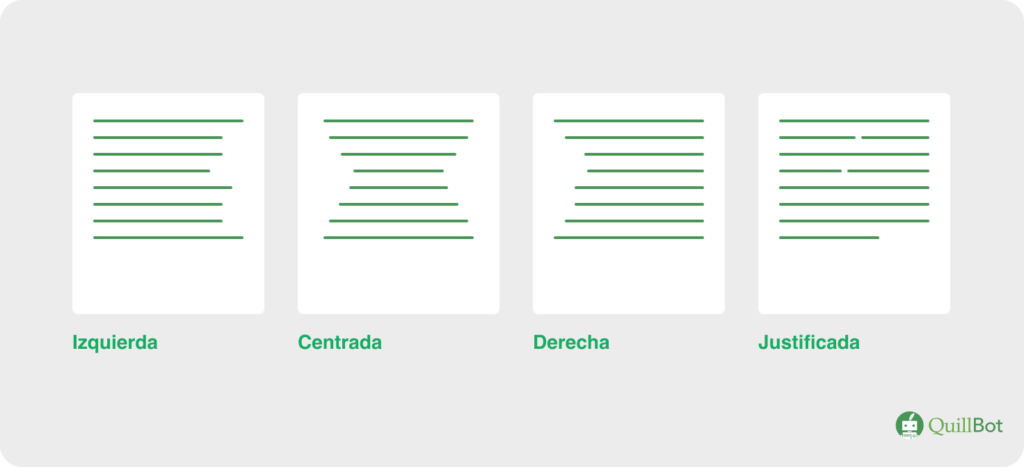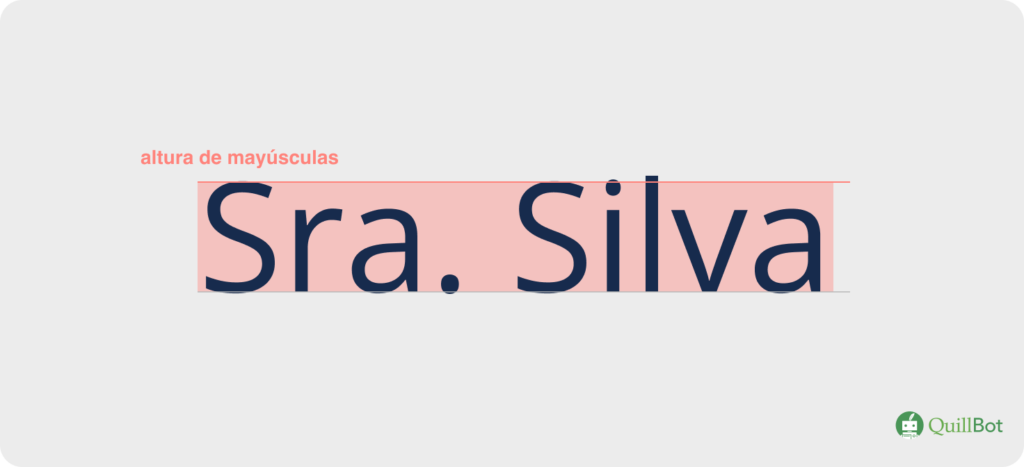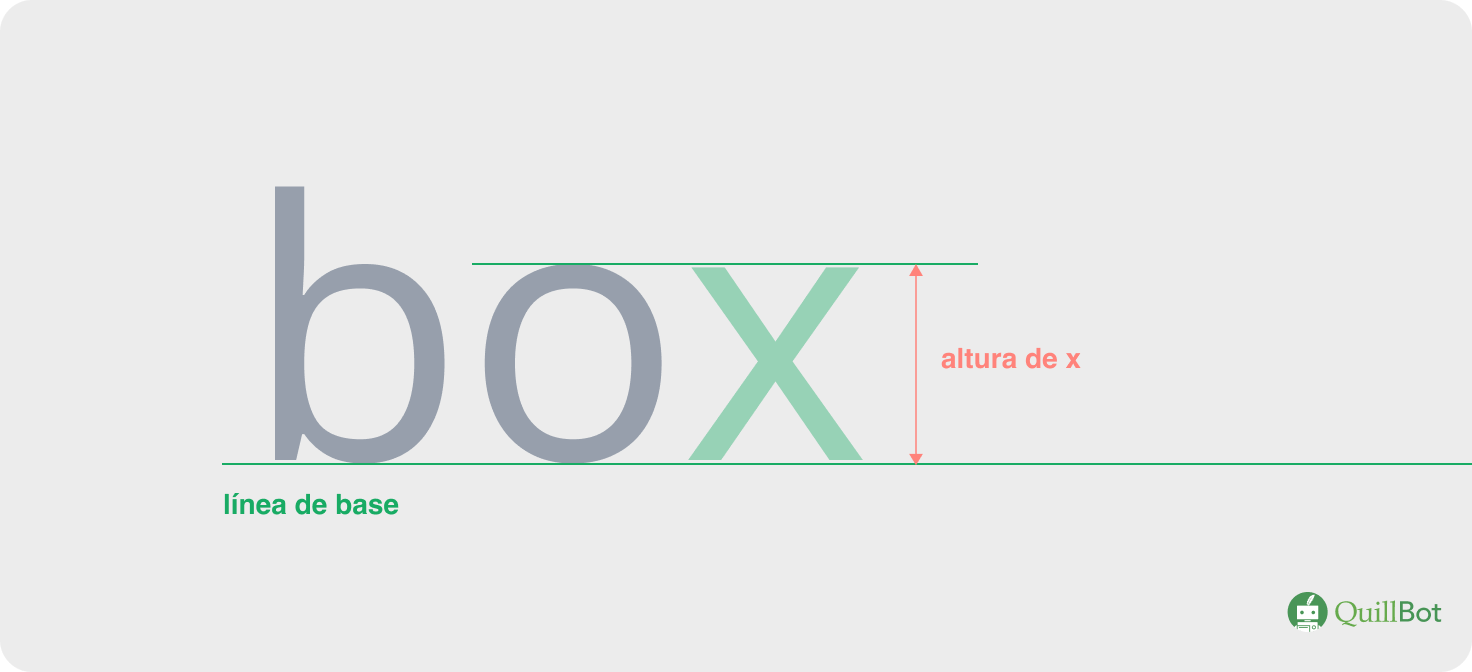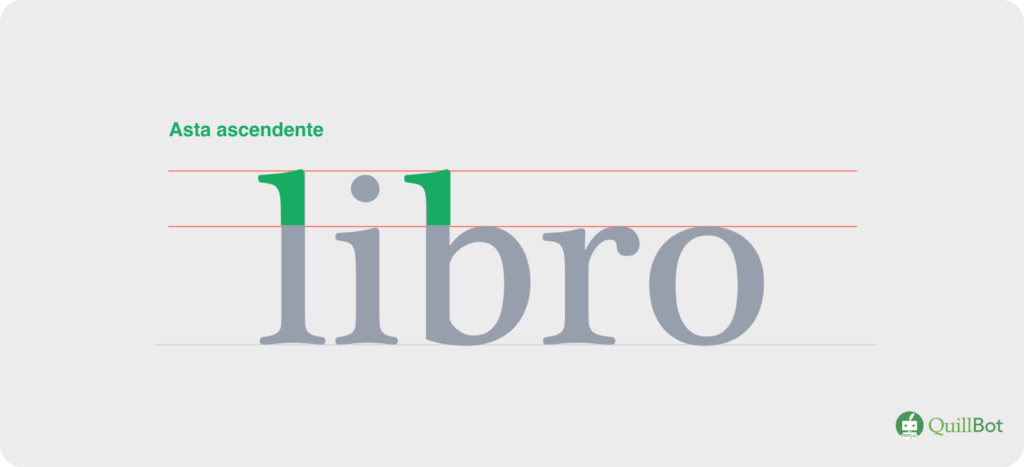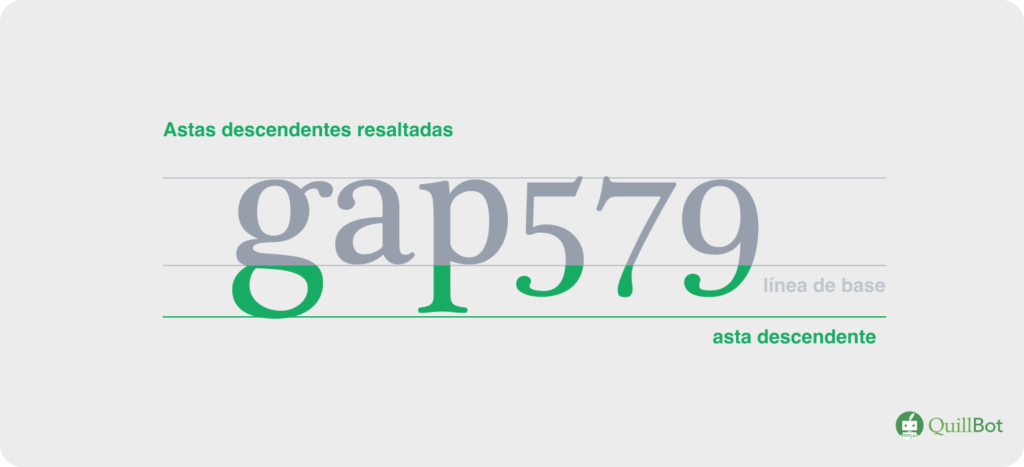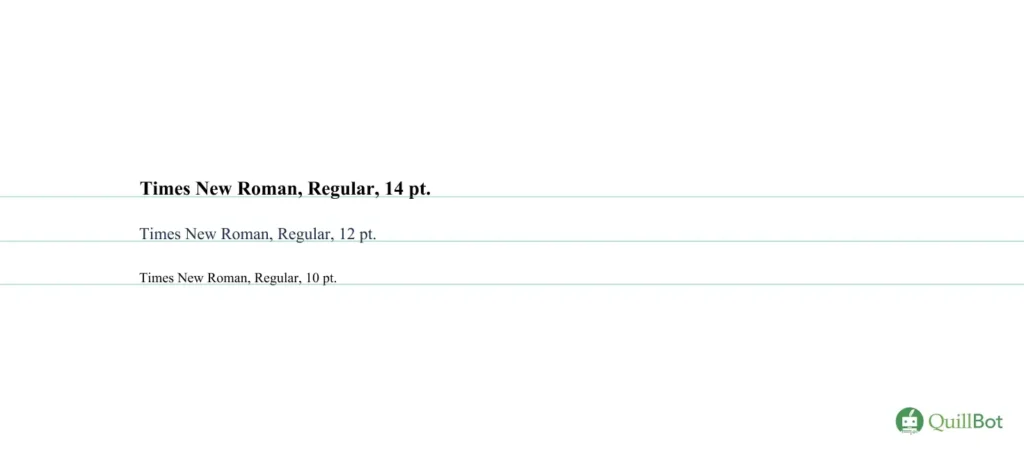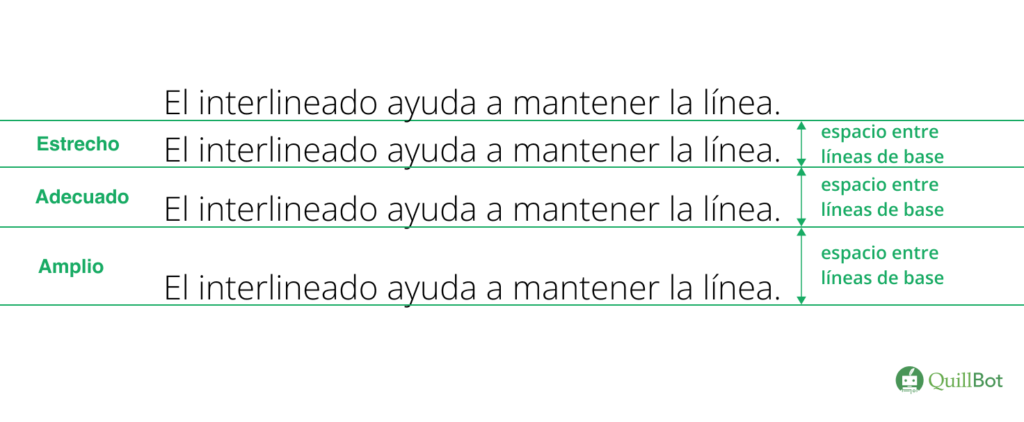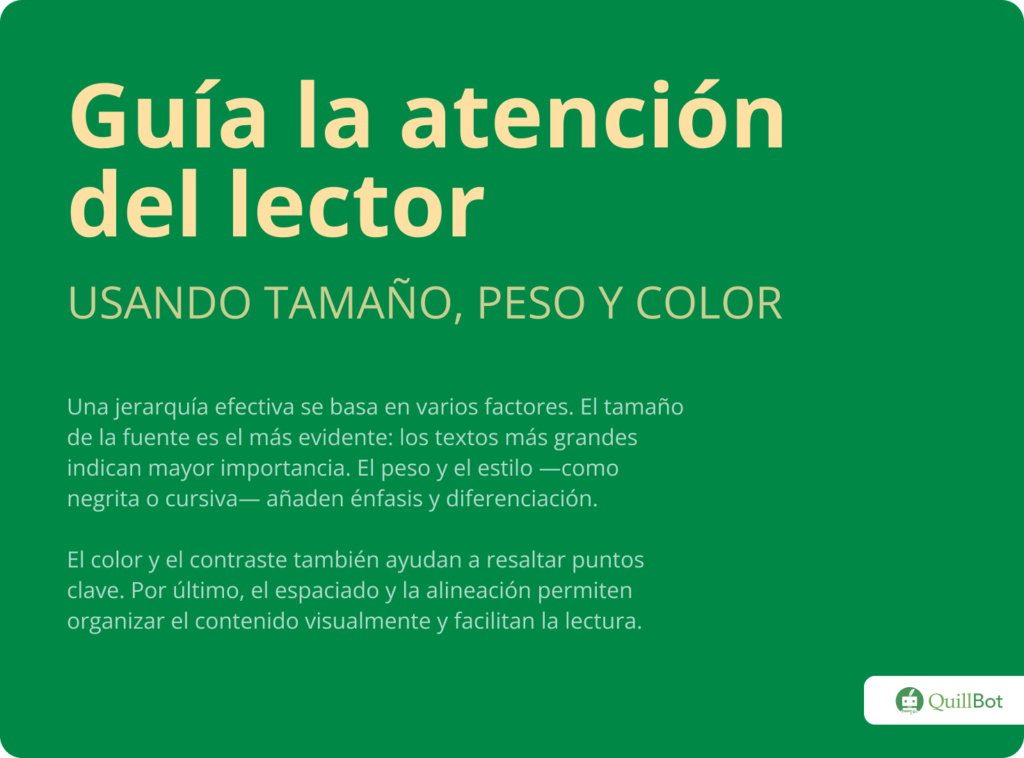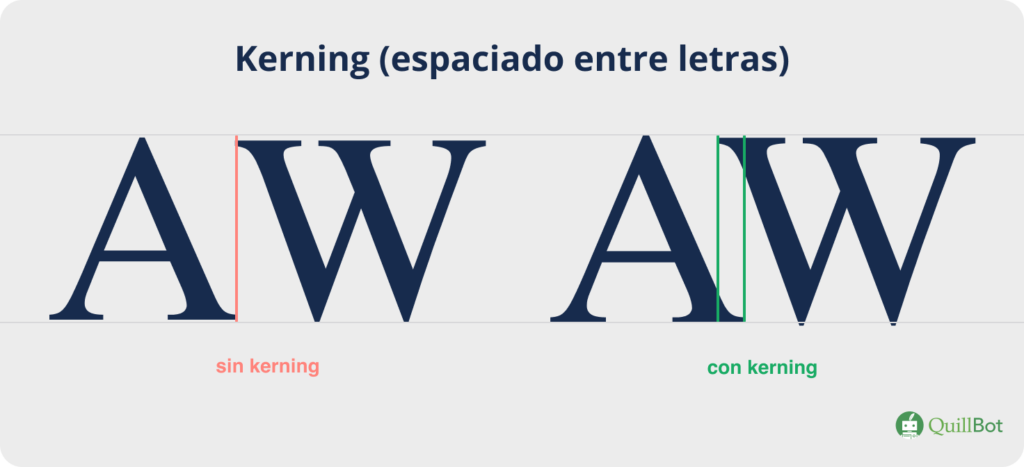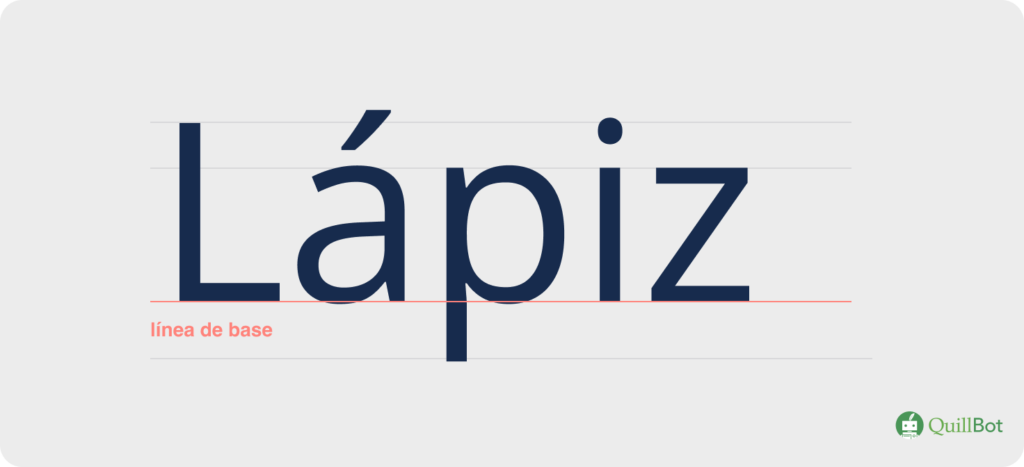
Tipografía | Significado, partes, tipos y ejemplos
La tipografía es un elemento clave de la comunicación visual; no se trata solo de elegir letras bonitas, sino de organizarlas para que la lectura sea fluida y natural. El diseño y la forma en que se presentan las palabras comunican tanto como el mensaje mismo.
Hoy la tipografía está en todas partes: desde un anuncio en una valla publicitaria hasta la interfaz de una app para hacer deporte.
Elegir la tipografía correcta no es solo estética; es uno de los factores que hace que un usuario permanezca en una página web o conecte con una marca.
Estos pequeños detalles pueden cambiar por completo la sensación que transmite un mensaje, ya sea en un libro o en una publicación de Instagram que busca captar la atención en pocos segundos.
Tipografía: significado y origen
El término tipografía es un helenismo derivado de las palabras griegas τύπος (“golpe” o “imprimir”) y γράφος (“escribir”).
Se refiere, etimológicamente, al arte de imprimir caracteres con los que se crean textos, técnica que es la base de lo que hoy llamamos tipografía.
La tipografía moderna parte del siglo XV, gracias a Johannes Gutenberg, el inventor de la imprenta de tipos móviles. Esto facilitó que se pudieran reproducir grandes cantidades de textos.
Hoy día, la tipografía es el arte y la técnica de elegir y disponer letras de modo que el lenguaje escrito sea fácil de leer, claro y visualmente atractivo.
La tipografía es el estilo visual, el diseño general de los caracteres (letras, números y símbolos).
La fuente es una versión específica de ese diseño.
Por ejemplo:
- Tipografía: Times New Roman (el estilo general)
- Fuente: Times New Roman negrita de 12 puntos (el diseño concreto)
Conceptos importantes de la tipografía
Es importante conocer algunos conceptos básicos de la tipografía que influyen en el diseño y en la legibilidad de un texto.
Algunos de estos conceptos son:
- Alineación
- Altura de mayúsculas
- Altura de x
- Asta ascendente
- Asta descendente
- Espaciado
- Fuente
- Interlineado
- Jerarquía
- Kerning
- Línea de base
- Longitud de línea
- Monoespaciado
- Peso
- Tracking
Alineación
La alineación es la forma en la que se organiza un texto respecto a los márgenes.
Existen cuatro tipos principales de alineación:
- Alineación a la izquierda: el texto empieza en el margen izquierdo y el derecho queda irregular. Es la alineación más común y fácil de leer.
- Alineación a la derecha: el texto termina en el margen derecho y el izquierdo queda irregular. Se usa en notas al pie o en diseños específicos.
- Alineación justificada: el texto se ajusta a ambos márgenes; todas las líneas tienen el mismo ancho. Crea bloques limpios, pero a veces quedan espacios entre palabras.
- Alineación centrada: cada línea del texto se centra respecto a un eje. Se usa en títulos, invitaciones o frases cortas.
Altura de mayúsculas
La altura de mayúsculas es la altura que alcanzan las letras mayúsculas desde la línea de base hasta su parte superior.
Altura de x
La altura de x es la altura de las letras minúsculas sin ascendentes ni descendentes. Se toma como referencia la letra “x”.
Asta ascendente
El asta ascendente es clave para diseñar o elegir fuentes. Es la parte de una letra minúscula que sobresale por encima de la altura media (la altura de la x).
Es el “palito” que sube en letras como: “b”, “d”, “h”, “k”, “l”.
Asta descendente
El asta descendente es la parte de una letra minúscula que se extiende por debajo de la línea de base, como: “g”, “j”, “p”, “q”, “y”.
Espaciado
El espaciado es el aire entre letras, palabras y líneas que hace que el contenido no se vea amontonado ni disperso.
Fuente
En tipografía, una fuente es el conjunto de caracteres (letras, números y símbolos) que comparten un mismo diseño, estilo y grosor.
Diferentes fuentes Times New Roman
Interlineado
El interlineado es el espacio entre una línea de texto y la siguiente.
- Interlineado pequeño: al estar las líneas muy juntas, puede dificultar la lectura de un texto.
- Interlineado grande: al estar las líneas de un texto muy separadas, puede romper la continuidad y hacer que el lector se pierda de una línea a otra.
- Interlineado adecuado: un espacio adecuado entre líneas mejora la legibilidad y evita que el lector se pierda entre líneas.
Jerarquía
La jerarquía es la forma en la que se organiza el contenido visualmente, guiando al lector para que entienda qué es más importante y en qué orden leerlo.
Kerning
El kerning es el ajuste del espacio entre pares de letras para que el texto se vea equilibrado.
En pares como “AV” o “WA”, las letras se suelen ver separadas si no se ajusta ese espacio.
Dentro de un texto, las letras cursivas se utilizan para aportar énfasis o diferenciar títulos de obras, citas o términos extranjeros.